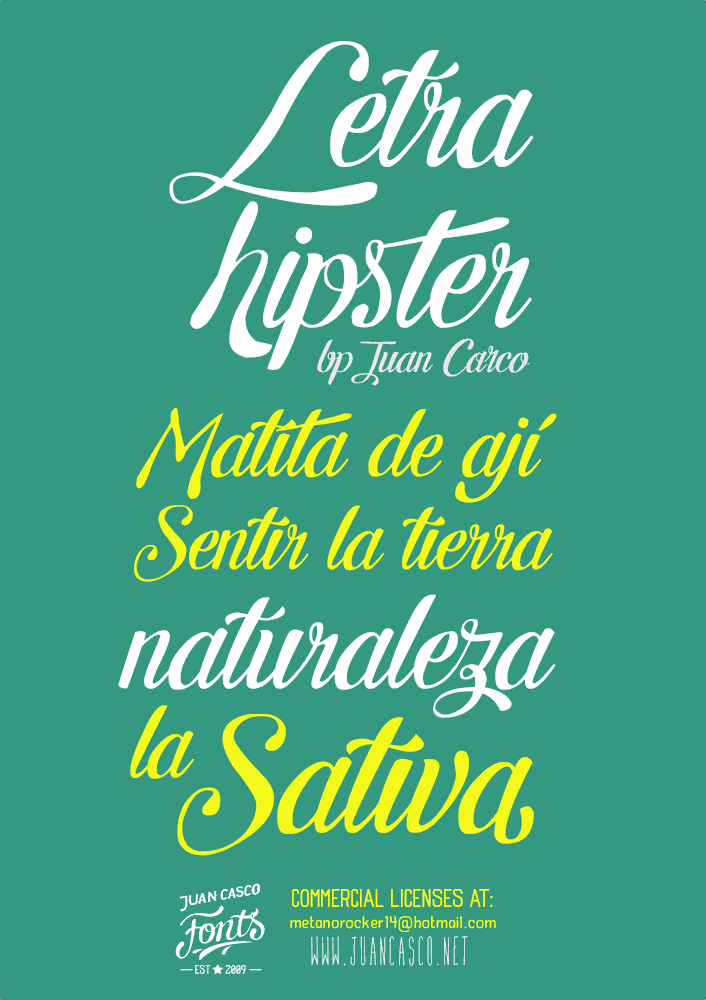
A Letra Hipster é uma fonte única que combina a essência autêntica do grafismo com as características distintas do hip-hop, criando uma impressão icônica e inconfundível. Ideal para quem procura uma maneira de dar um toque único aos seus projetos pessoais ou comerciais, esta fonte é perfeita para anúncios, selos e até mesmo para criar logotipos exclusivos que chamam a atenção. O designer Juan Casco traz sua habilidade única para desenvolver uma tipografia que captura o espírito de um estilo de vida vibrante. A Letra Hipster é mais do que apenas letras – ela transmite os sentimentos e ideias que definem este movimento cultural, com suas linhas elegantes e personalizadas. Se você está procurando por algo singular para a sua marca ou projeto pessoal, a fonte Letra Hipster pode ser o elemento perfeito. Para qualquer uso comercial, é necessário entrar em contato conosco através do email ou visitar nosso site oficial. Através de uma conexão direta com Juan Casco e seu trabalho inovador, você terá todo o apoio necessário para explorar a Letra Hipster Font sem limitações.
Designer: Juan Casco